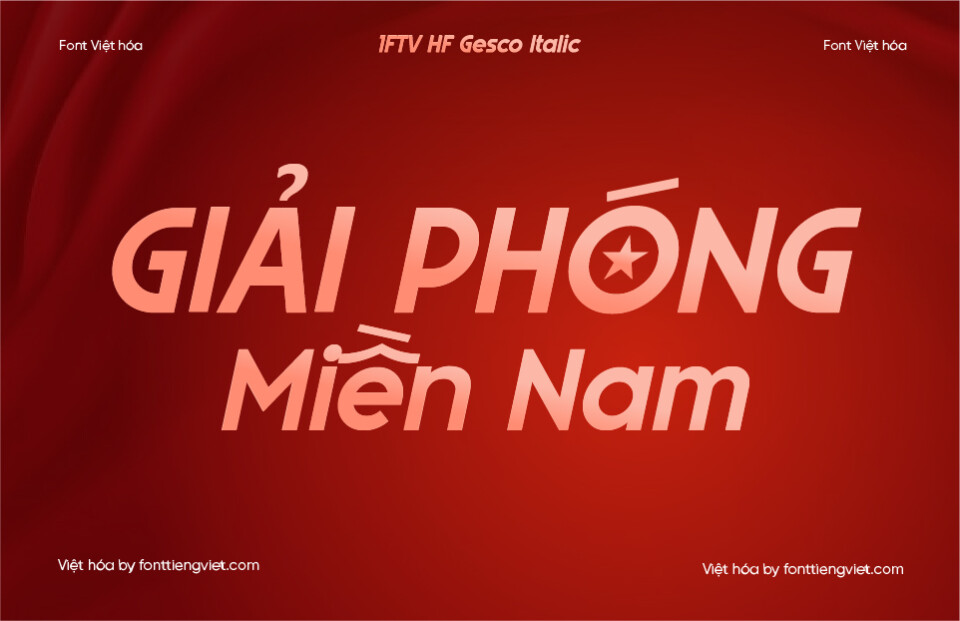
Font Việt hóa 1FTV HF Gesco Italic – Font không chân nghiêng hiện đại cho thiết kế dịp Tết, dịp lễ
Giới thiệu về Font Việt hóa 1FTV HF Gesco Italic – Font không chân nghiêng hiện đại cho thiết kế dịp Tết, dịp lễ
Trong bối cảnh thị trường thiết kế đồ họa tại Việt Nam ngày càng phát triển, việc tìm kiếm một bộ Font Miễn Phí chất lượng cao luôn là ưu tiên hàng đầu của các bạn trẻ và nhà thiết kế chuyên nghiệp. Đặc biệt, khi các mùa lễ hội đang đến gần, sự xuất hiện của Font Việt hóa 1FTV HF Gesco Italic – Font không chân nghiêng hiện đại cho thiết kế dịp Tết, dịp lễ đã mang đến một làn gió mới đầy cảm hứng. Đây là một bộ font chữ thuộc phong cách Sans-serif (không chân) với dáng nghiêng Italic đầy năng động, giúp các bản thiết kế trở nên thanh thoát và chuyên nghiệp hơn bao giờ hết. Được tinh chỉnh kỹ lưỡng về dấu tiếng Việt, bộ font này đảm bảo tính thẩm mỹ tuyệt đối khi hiển thị trên cả nền tảng in ấn lẫn kỹ thuật số.
Ưu điểm nổi bật của Font Việt hóa 1FTV HF Gesco Italic trong thiết kế
Phong cách hiện đại và tinh tế
Font Việt hóa 1FTV HF Gesco Italic – Font không chân nghiêng hiện đại cho thiết kế dịp Tết, dịp lễ nổi bật với các đường nét dứt khoát, gọn gàng và tối giản. Khác với các bộ font truyền thống thường tạo cảm giác cứng nhắc, phiên bản Italic của Gesco mang lại sự mềm mại, uyển chuyển nhờ góc nghiêng hoàn hảo. Điều này giúp các biểu ngữ, poster hay thiệp chúc mừng trở nên bắt mắt và dễ tiếp cận hơn với người xem. Các bạn học sinh, sinh viên có thể dễ dàng ứng dụng bộ font này vào các bài thuyết trình hay thiết kế báo tường để tạo điểm nhấn khác biệt và hiện đại.
Tối ưu hóa cho các dự án lễ hội tại Việt Nam
Vào những dịp quan trọng như Tết Nguyên Đán hay các ngày lễ lớn, nhu cầu truyền tải thông điệp vui tươi, tràn đầy năng lượng là rất lớn. Bộ font này được thiết kế để chịu được các kiểu bố cục đa dạng, từ tiêu đề lớn đến các đoạn mô tả ngắn. Sự thanh lịch của nó giúp giữ được nét trang trọng của ngày Tết truyền thống nhưng vẫn không kém phần thời thượng, phù hợp với xu hướng thẩm mỹ của thế hệ mới. Khả năng hiển thị tiếng Việt chuẩn xác, không lỗi dấu chính là điểm cộng lớn nhất giúp người dùng tiết kiệm thời gian chỉnh sửa.
Ứng dụng Font Việt hóa 1FTV HF Gesco Italic – Font không chân nghiêng hiện đại cho thiết kế dịp Tết, dịp lễ vào thực tế
Thiết kế truyền thông và quảng cáo
Với độ dày vừa phải và độ nghiêng tinh tế, font chữ này cực kỳ phù hợp cho các chiến dịch marketing mùa lễ hội. Bạn có thể sử dụng nó cho các bài đăng trên mạng xã hội, banner website hoặc hình ảnh quảng bá sản phẩm Tết. Cấu trúc không chân giúp chữ đọc rõ ràng ngay cả ở kích thước nhỏ, đảm bảo thông điệp của bạn luôn được truyền tải trọn vẹn đến khách hàng.
Làm thiệp chúc mừng và quà tặng
Việc tự tay thiết kế những tấm thiệp ý nghĩa cho người thân và thầy cô sẽ trở nên đơn giản hơn với Font Việt hóa 1FTV HF Gesco Italic – Font không chân nghiêng hiện đại cho thiết kế dịp Tết, dịp lễ. Bạn có thể kết hợp font này với các gam màu đỏ, vàng đặc trưng của mùa xuân để tạo nên những tác phẩm đậm chất nghệ thuật. Sự hiện đại của font chữ sẽ làm cho món quà của bạn trở nên độc đáo và ấn tượng hơn trong mắt người nhận.